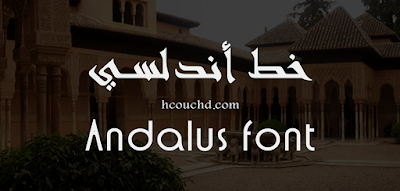
الأندلس كانت المعروفة أيضا في الخطاب الشعبي الغربي خصوصا و العربي و الإسلامي أحيانا باسم «إسپانيا الإسلامية» أو «أيبيريا الإسلامية»، هذه الاخيرة كانت المعروفة بتصاميمها الزخرفية .
خط خط أندلسي خط إحترافي و رائع ، يصنف من الخطوط البسيطة، تتجلى قوته في بساطته ، يمكنك تحميل هذا خط من رابط أسفله …